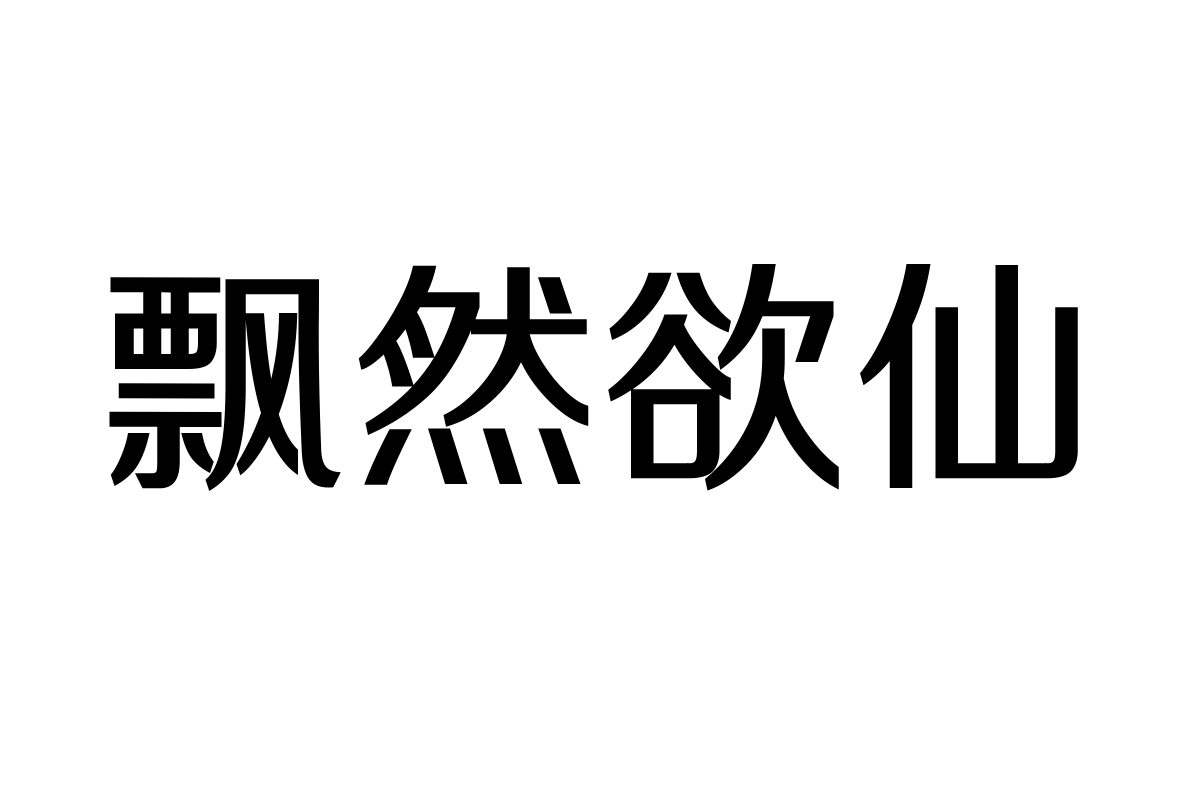
三极清韵简体字体是一款现代简约风格的中文字体,具有独特的艺术美感和优雅的书写效果。这款字体采用了简洁而流畅的线条设计,使得文字呈现出一种轻松愉悦的氛围。同时,三极清韵简体字体还注重细节的处理,如笔画的粗细、间距的均匀度等,都经过精心的调整和优化,使得整体效果更加和谐美观。此外,这款字体还具有较强的可读性和适应性,适用于各种场景和场合,无论是用于标题、正文还是装饰元素,都能展现出其独特的魅力。